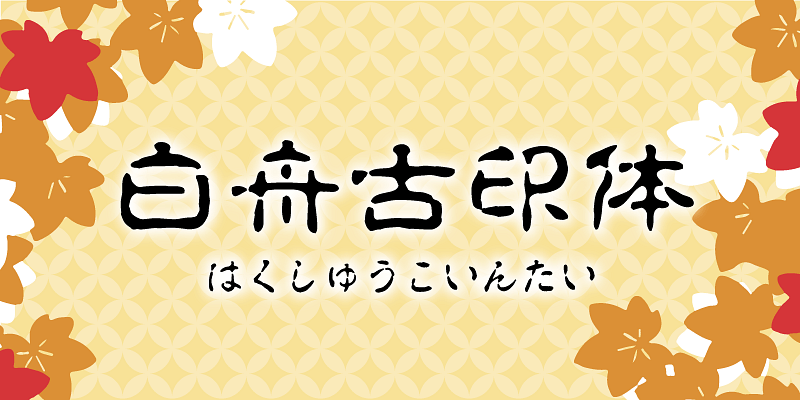
Grâce à notre expérience en tant qu’atelier de fabrication de sceaux, nous avons créé cette police dans le style antique kointai utilisé pour les sceaux depuis de nombreuses années.